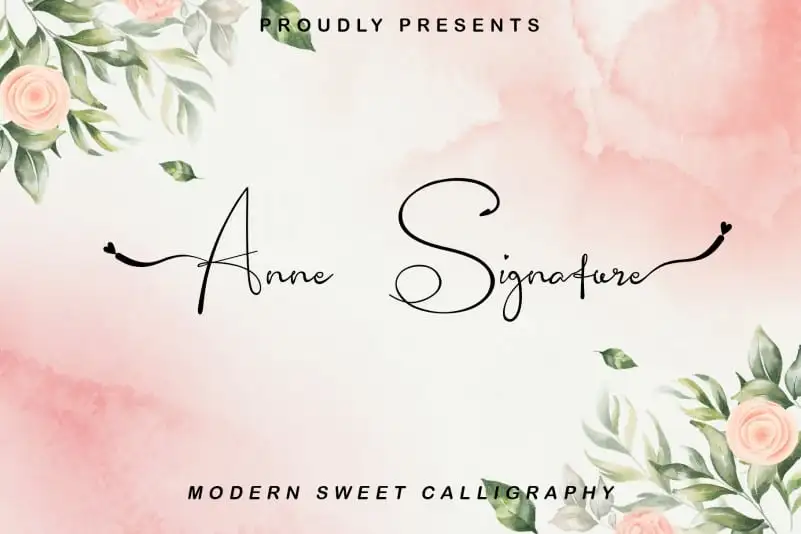
Anne Signature Script Font – Download Grátis
Aproveite a oportunidade única para adicionar um toque exclusivo e elegante ao seu trabalho com Anne Signature Script Font. Esta fonte foi criada para designers que buscam uma maneira de incorporar elementos artesanais e sutis em seus projetos, seja eles aqueles destinados a logomarcas e identificações visuais, invitações personalizadas ou até mesmo embalagens de produtos. Com um estilo elegante e um toque natural nos traços de escrita, Anne Signature Script Font é perfeita para qualquer necessidade que exigir uma mão escritora delicada. Seja você criando o famoso e tradicional “watermark” no seu trabalho fotográfico ou personalizando sua marca de logo com um toque artesanal, a Anne Signature Script Font está aqui para tornar tudo mais único. Suas possibilidades são limitadas apenas pelo seu próprio imaginário. Adicione nuances humanizadoras a suas criações digitais, mantenha-se fiel aos seus valores e paixões através da inclusão de um design original em sua identidade visual ou use-a como uma fonte de inspiração para criar produtos que ressoem com o público. Experimente Anne Signature Script Font hoje e dê vida à sua arte digital, trazendo a sensação de escrita real ao seu trabalho.